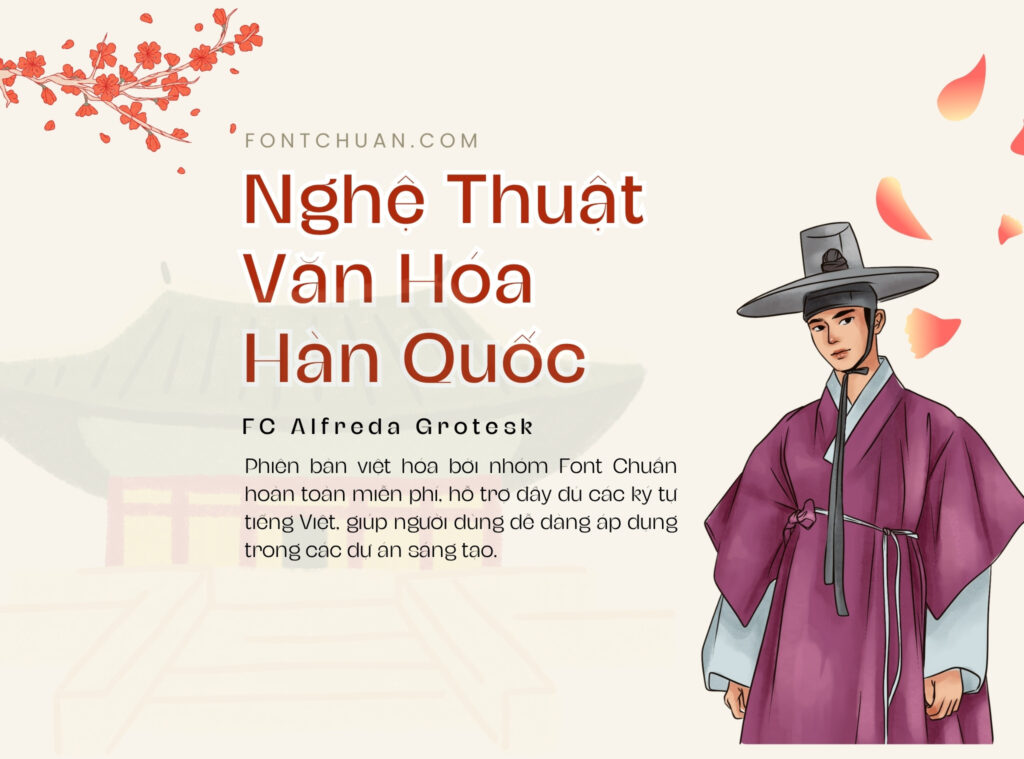
Alfreda Font là một phông chữ sans-serif độc đáo được thiết kể bởi Santi Rey, kết hợp giữa các nét có độ dày đồng đều và không đồng đều, cùng với sự pha trộn giữa tương phản tự nhiên và ngược. Thiết kế mang đến cảm giác nhân văn với các chi tiết tinh tế, tạo nên sự khác biệt so với các phông chữ grotesque thông thường. Phông chữ này bao gồm 6 trọng lượng, có hơn 400 ký tự và 18 bộ kiểu dáng, phù hợp cho nhiều mục đích sử dụng khác nhau. Font này có thể được dùng làm Font ngày Nhà giáo Việt Nam để tạo nên các ấn phẩm trang trọng, ý nghĩa và phù hợp với tinh thần của ngày lễ đặc biệt.
FC Alfreda Grotesk là phiên bản việt hóa mới và miễn phí bởi nhóm Font Chuẩn hoàn toàn miễn phí, hỗ trợ đầy đủ các ký tự tiếng Việt, giúp người dùng dễ dàng áp dụng trong các dự án sáng tạo. Hiện nay trên thị trường phiên bản SVN-Alfreda và phiên bản khác có thể tốn phí.